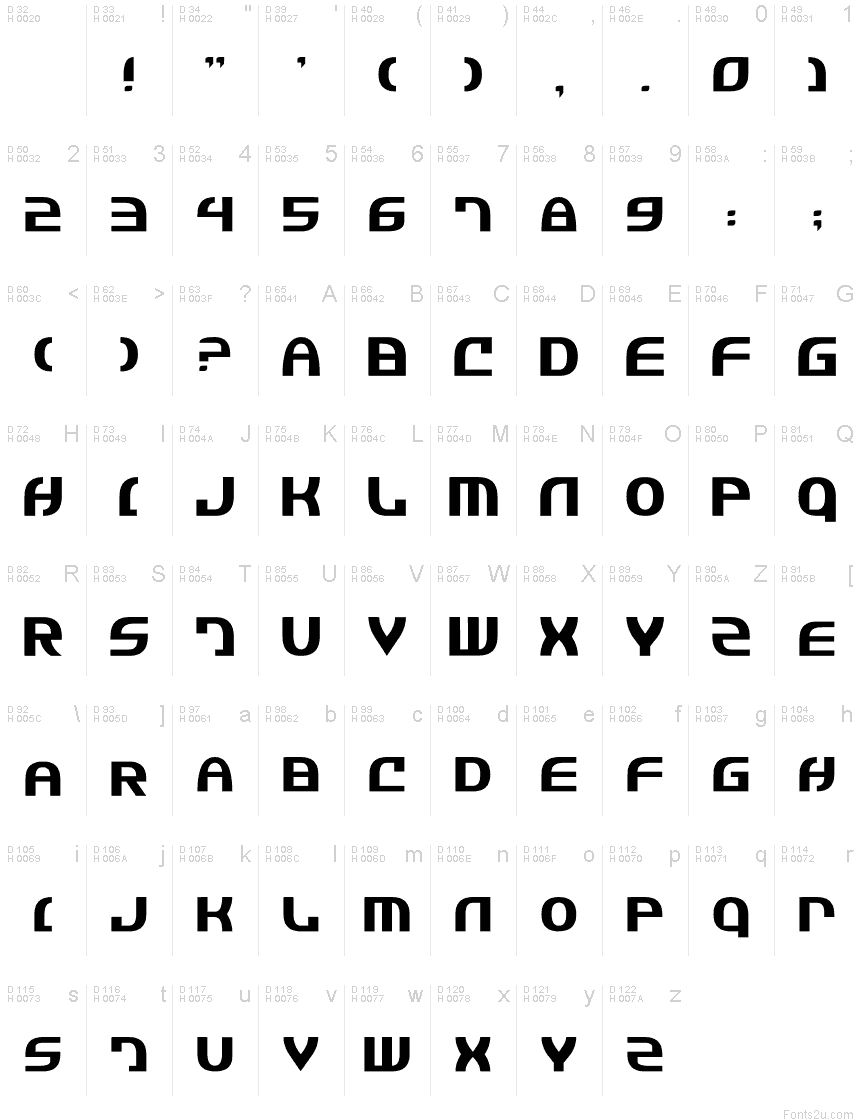
Jannisary Sword von Iconian Fonts ist eine kostenlose, futuristische Display-Schrift, die wirkt, als wäre sie aus einem einzigen Stück glänzendem Metall geschnitten. Kräftige Vertikale fallen gerade ab und biegen sich dann in elegante, eckige Bögen – das verleiht jedem Wort einen starken Sci-Fi-Logo-Look. Durch die engen Abstände und geschmeidigen, durchgehenden Striche wirkt das Schriftbild wie ein technisches Band, das besonders in großen Größen fett und unverwechselbar hervorsticht.
Mit Jannisary Sword setzen Sie Titel für Gaming-Logos, Sci-Fi-Filmplakate, E-Sport-Branding, Tech-Konferenz-Banner, Albumcover und YouTube-Intros perfekt in Szene. Diese kostenlose Schrift glänzt dort, wo Sie ein selbstbewusstes, zukunftsorientiertes Wortbild benötigen, das konstruiert statt handgeschrieben wirkt. Kombinieren Sie sie mit einer klaren, geometrischen Grotesk für den Fließtext und lassen Sie Jannisary Sword die lauten, filmreifen Momente übernehmen.
Jannisary Sword